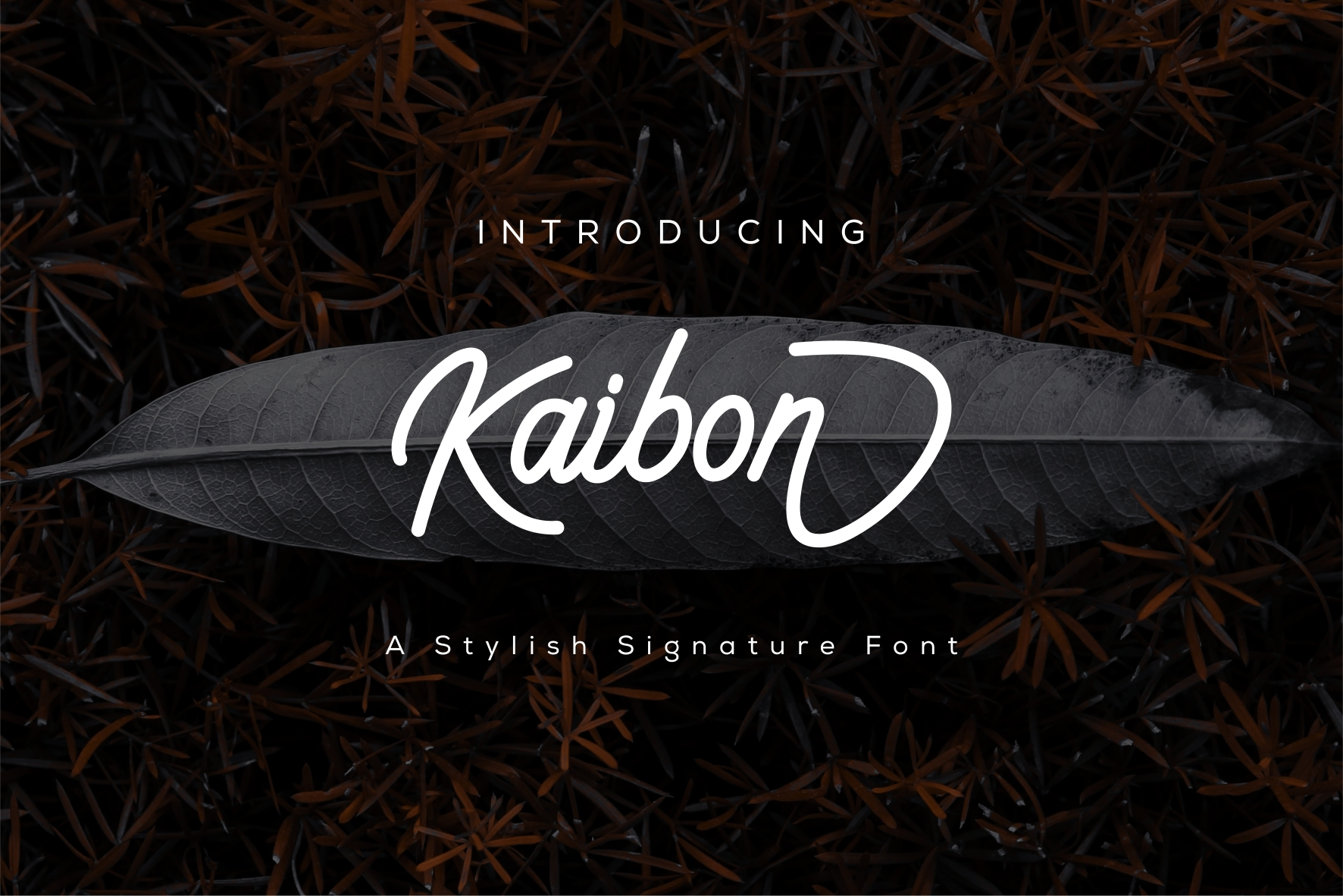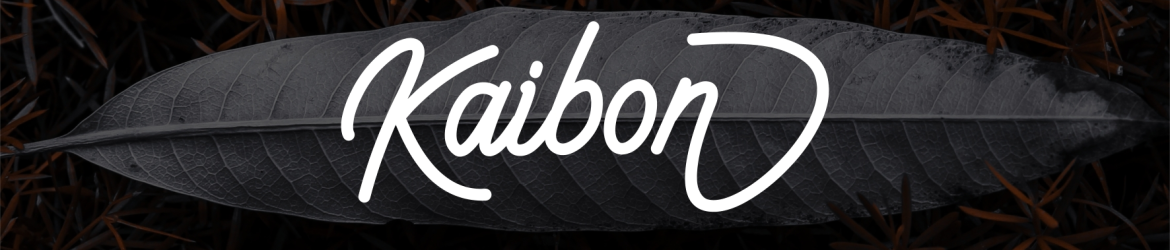
Kaibon Signature Font – Download Grátis
A Kaibon Signature Font é uma escolha perfeita para qualquer designer que busca uma fórmula elegante e feminina para seus projetos digitais. Esta fonte, moderna e estilizada, transmite um toque sofisticado e delicado que se destaca em diversos aplicativos gráficos. Perfeita para criações de marca, logotipos, cartões de convidados de casamento, editoriais de revistas, frases motivacionais ou postagens publicitárias, folheto de eventos e muito mais. Com sua elegância contida e seu ar refinado, a Kaibon Signature Font é uma escolha ideal para qualquer projeto que busque um toque pessoal em seus materiais de comunicação visual.